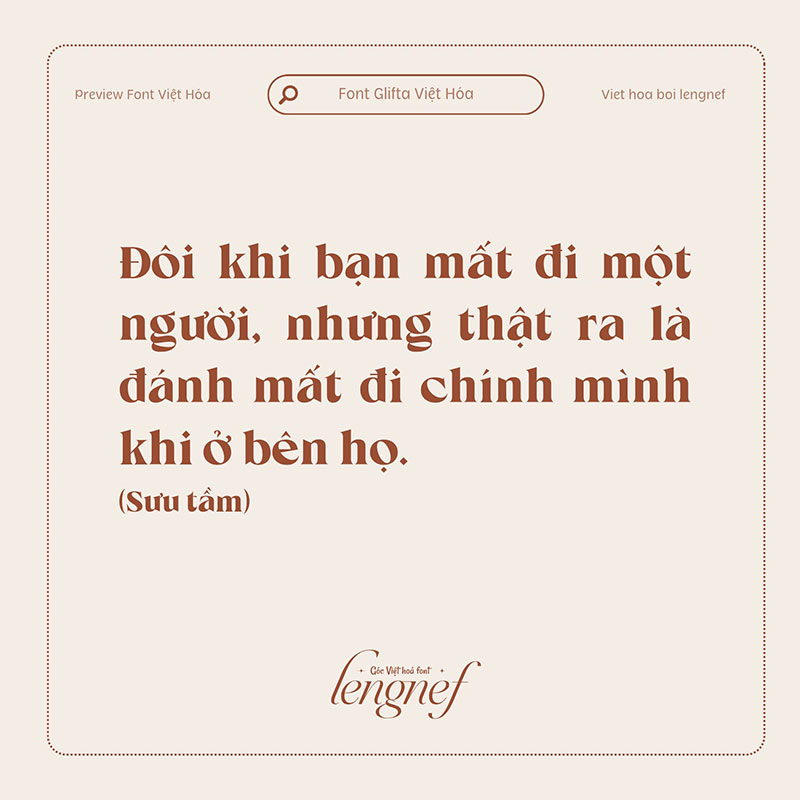
• Tác giả: The Native Saint Club
• Việt hóa: lengnef
Font LF Glifta
Glifta – Phông chữ serif hiện đại với hai style regular và italic có thể dùng cho nhiều dự án thiết kế khác nhau. Phông chữ này tạo ấn tượng mạnh mẽ và đậm nét, mang đến cảm giác nổi bật. Phù hợp cho mọi dự án như: logo, dự án thương hiệu, bao bì sản phẩm, trích dẫn, áp phích và bất kỳ dự án đẹp nào cần một phong cách serif mạnh mẽ và nổi bật.